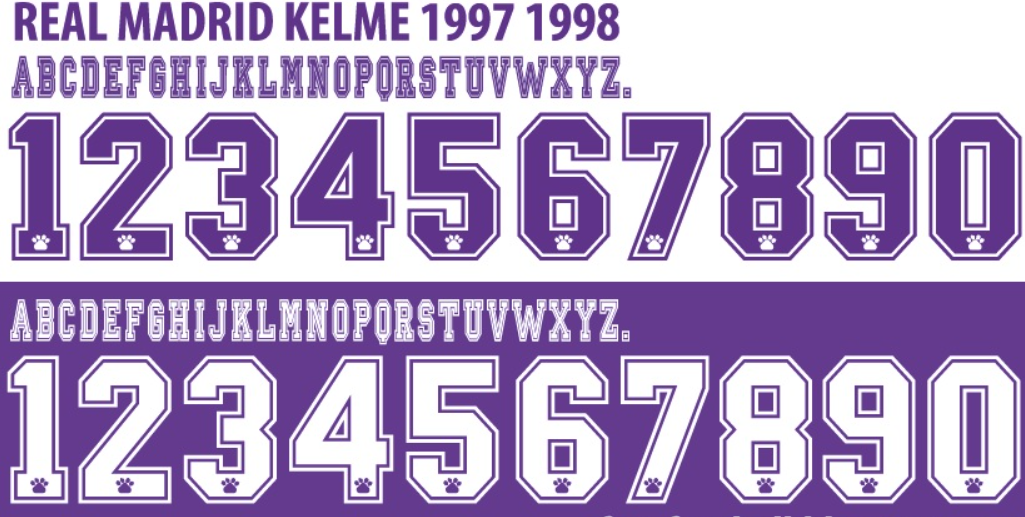
Se você é apaixonado por camisas retrô e pela história do futebol europeu, este arquivo é obrigatório na sua coleção. Estamos disponibilizando a tipografia clássica usada pelo Real Madrid durante o final dos anos 90 e a virada do milênio, um período dourado que culminou na conquista da oitava Champions League.
Esta é a fonte que estampou as costas de lendas como Raúl, Roberto Carlos, Redondo, Morientes e o jovem Casillas. É a oportunidade perfeita para recriar o visual nostálgico da era em que a Adidas consolidava sua parceria histórica com o clube merengue e o patrocínio da Teka brilhava no peito.
- Usos Recomendados: Sublimação de camisas retrô (tailandesas ou réplicas), personalização de kits em games (PES/FIFA) e criação de pôsteres nostálgicos.
Estilo Visual e Nostalgia
A tipografia do Real Madrid entre as temporadas 1998, 1999 e 2000 reflete o design de transição do final do século XX. É uma fonte robusta, com excelente legibilidade e um peso visual que impõe respeito.
Diferente das fontes minimalistas atuais, o estilo dessa época (muitas vezes aplicado em preto ou azul escuro sobre o branco) possui um acabamento clássico, sem serifas exageradas, mas com uma geometria sólida. Ela é sinônimo da classe de Raúl González finalizando na grande área. Ideal para quem quer reproduzir fielmente os uniformes da La Liga ou da final da UCL em Paris (2000).
Dica de Personalização: Para um visual 100% autêntico, combine esta fonte com a aplicação do logo da Adidas antigo e o patrocínio da Teka centralizado.